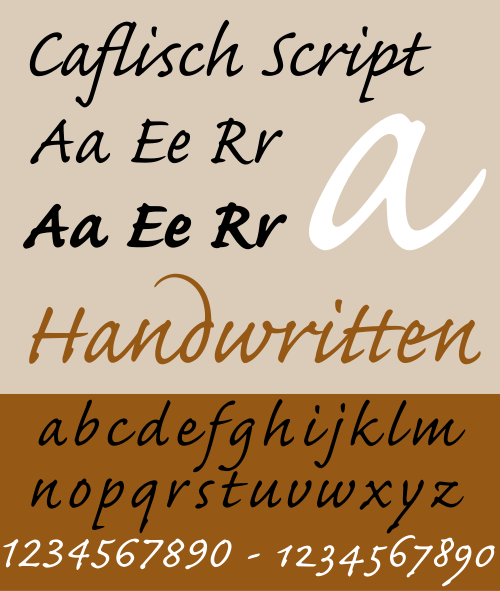
スクリプト書体は、手書きによって生み出される多様で流動的なストロークに基づいています。[1] [2]スクリプト書体は、ラテンアルファベットの本文の拡張テキストではなく、一般に展示用または商用印刷に使用されます。一部のギリシャ語アルファベット書体は、特に歴史的に、手書きをより忠実に模倣してきました。
スタイル
スクリプト書体は、筆記体に似た非常に規則的なフォーマルな書体と、より緩やかでカジュアルな書体に分類されます。
正式なスクリプト
正式な書体の大部分は、ジョージ・ビックハム、ジョージ・シェリー、ジョージ・スネルといった 17 世紀と 18 世紀の書家の書体に基づいています。文字の本来の形は、羽ペンまたはペンの金属ペン先で生成されます。どちらも細い線と太い線を作成できます。彼らの書体に基づいた書体は、18 世紀後半から 19 世紀初頭にかけて登場しました。正式な書体の現代的な復活は、クエンストラー スクリプトとマシュー・カーターの書体であるスネル ラウンドハンドに見ることができます。これらの書体は、高級感と優雅さを演出するために、招待状や卒業証書によく使用されます。文字をつなげるために 活字の合字が使用されることもあります。
カジュアルなスクリプト
カジュアルなスクリプトは、よりフォーマルではなく、よりアクティブな手書きを表現します。ストロークの幅はさまざまですが、ペン先ではなく濡れたブラシで書かれたように見えることがよくあります。カジュアルなスクリプトは 20 世紀初頭に登場し、1950 年代初頭に写真植字が登場すると、その数は急速に増加しました。ヨーロッパや北米では1970 年代まで広告でよく使用されていました。カジュアルなスクリプトの種類の例としては、Brush Script、Kaufmann、Mistral などがあります。Freestyle Scriptのように、接続されていないものもあります。
テクノロジー
筆記体書体では、文字が手書きのようにつながって変化することを意図している場合、印刷技術に特別な要求が課される。クロード・ガラモンドのgrecs du roi書体のような手書きを模倣した書体では、多くの代替文字が必要になる。デジタル書体では、これらの代替文字は (一度描画すれば) InDesign などのアプリケーションで文脈上の合字を挿入することでシームレスに置き換えることができるが、金属書体ではこれは複雑だった。金属書体のもう 1 つの複雑さは、書体がかみ合うために繊細な張り出し部分が必要であることである。このため、書体が隙間なくぴったりと収まるように、また書体が壊れたり、紙の上でインクが自然に広がることで隙間が埋まったりしないように、慎重な設計と鋳造が必要だった。[4] [5]
スクリプト書体は、技術の発達と金属活字の広範な使用の終焉により、20世紀後半に急速に進化しました。歴史的に、ロゴ、ディスプレイ、店舗正面の看板のほとんどはフォントを使用しておらず、看板職人や彫刻家が作成したカスタムデザインのレタリングでした。[6] [7] [8] [9]写真植字、そしてコンピューターによって、金属活字の時代よりもはるかに簡単にさまざまなサイズでテキストを印刷できるようになったため、企業がロゴや看板に手描きのレタリングではなく活字を使用することがますます一般的になっています。さらに、写真植字により、金属活字では非常に複雑な文字の重なりが比較的簡単になりました。マシュー・カーターは、 1966年のスネル・ラウンドハンド書体は、金属ではシミュレートするのが難しいカリグラフィのスタイルを意図的に再現するように設計されたと述べています。 [10] [11]より洗練された筆記体フォントを可能にするさらなる開発として、OpenType形式のリリースがあり、現在ほとんどのフォントはこの形式でリリースされています。これにより、フォントの文字セットが大きくなってデザインの洗練度が増し、文脈挿入が可能になり、互いに一致する文字が自動的に文書に挿入されるので、ユーザーが手動で正しい代替文字を選択しなくても、フォントが手書きを忠実に模倣できるようになります。[12]多くの現代の筆記体書体は、さまざまな歴史的時代の手書きレタリングのスタイルを模倣しています。
ユニコード
通常のほとんどの使用法では、表示方法に関係なく、通常のテキストの通常の英数字コードポイントを使用する必要があります。スクリプトの表示方法は、たとえばhtml span style="font-family=コマンドを使用して指定します。
数学的な用途には、大文字と小文字の両方を含む専用のコードポイントのセットがあります。52 文字すべてをサポートするフォントはほとんどなく、その表示スタイルはラウンドハンドからチャンセリーハンドなど多岐にわたります。
これらの文字は次のとおりです: 𝒜ℬ𝒞𝒟ℰℱ𝒢ℋℐ𝒥𝒦ℒℳ𝒩𝒪𝒫𝒬ℛ𝒮𝒯𝒰𝒱𝒲𝒳𝒴𝒵 𝒶𝒷𝒸𝒹ℯ𝒻ℊ𝒽𝒾𝒿𝓀𝓁𝓂𝓃ℴ𝓅𝓆𝓇𝓈𝓉𝓊𝓋𝓌𝓍𝓎𝓏
- 一部の文字は Unicode では「SCRIPT ...」という名前が付けられています。
- U+2113 ℓ スクリプト小文字 L ( ℓ )
- U+2118 ℘ SCRIPT CAPITAL P ( ℘, ℘ ) (実際には誤称で、名前はWEIERSTRASS ELLIPTIC FUNCTIONに修正されています)